Sekarang font tidak hanya berupa abjad, angka dan simbol saja; tapi juga bisa berbentuk icon dan pattern, seperti 18 font yang disajikan di artikel ini.
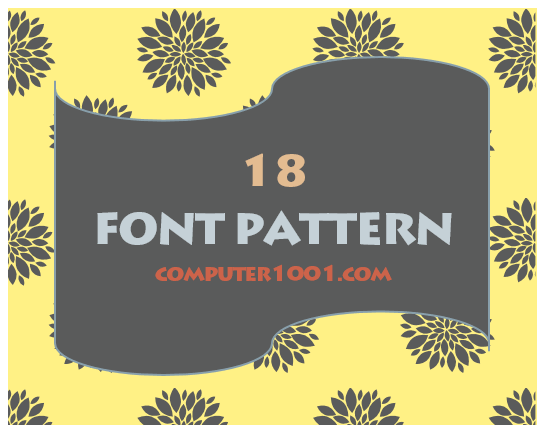
Font dingbat berbentuk aneka motif atau corak ini bisa kita gunakan sebagai background pada wallpaper serta sebagai hiasan pada desain cover laporan, label, menu, packaging, kartu nama, undangan, dan lain-lain.
Jadi bila biasanya Anda mendesain dengan menggunakan gambar JPG, GIF atau PNG; maka coba juga menggunakan font berbentuk pattern. Keuntungan menggunakan font pattern adalah kemudahan mengubah warna, ukuran dan transparansi.
Berikut adalah contoh desain yang dibuat Computer 1001 di Microsoft Word dengan menggunakan font pattern sebagai hiasan.
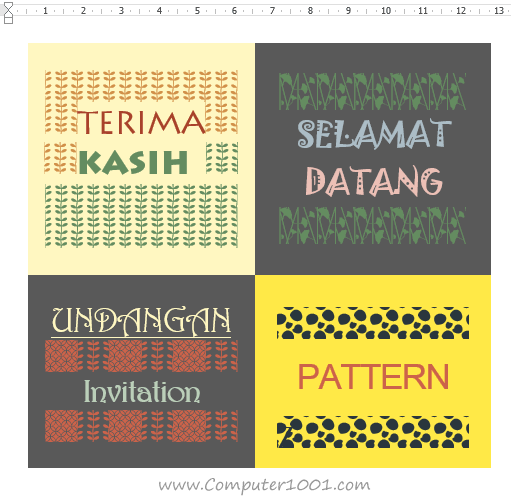
Cara Menggunakan Font Pattern
Penggunaan font pattern sama dengan font yang lain. Bila menggunakannya di Text Box atau Shape aplikasi Microsoft Office (Word, Excel, PowerPoint); kita mungkin ingin mengatur lagi margin-nya agar tampilan font lebih menyatu dengan pinggiran kotak.
18 Font Pattern
- Peoni Patterns
- Patterns
- Typo Backgrounds
- KleinKarpets
- Serangkaian Pattern
- Square Things
- Square Things 2
- Symmetry
- Bricks n Things
- Grids n Things
- Haus Ethnik Dingbats Font
- Pattern Typeface (free)
- Ikatan Font
- Afrika Gold A Patterns Font
- AfricanPattern Font
- Amish Quilts Font
- Formas Geometricas 2
- IronGlass DropCaps